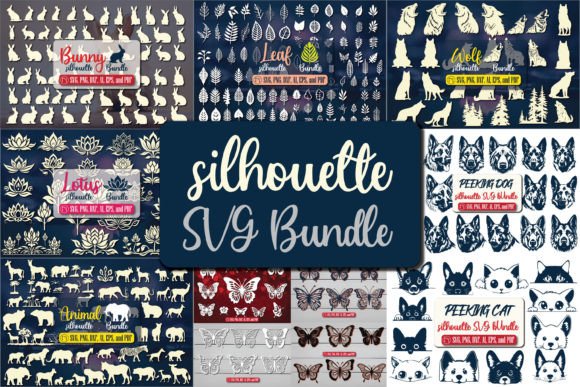
Cricut Silhouette SVG Mega Bundle
Att hitta rätt designelement kan vara utmanande, men Cricut Silhouette SVG Mega Bundle erbjuder en exceptionell samling som omedelbart lyfter ditt arbete.
Tillverkad med precision, ger Cricut Silhouette SVG Mega Bundle rena vektorer, smidig typografi och en kommersiell licens för sinnesfrid.
Oavsett om du skapar POD-produkter (Print on Demand), bröllopsinbjudningar eller grafik för sociala medier, är Cricut Silhouette SVG Mega Bundle ett perfekt val.